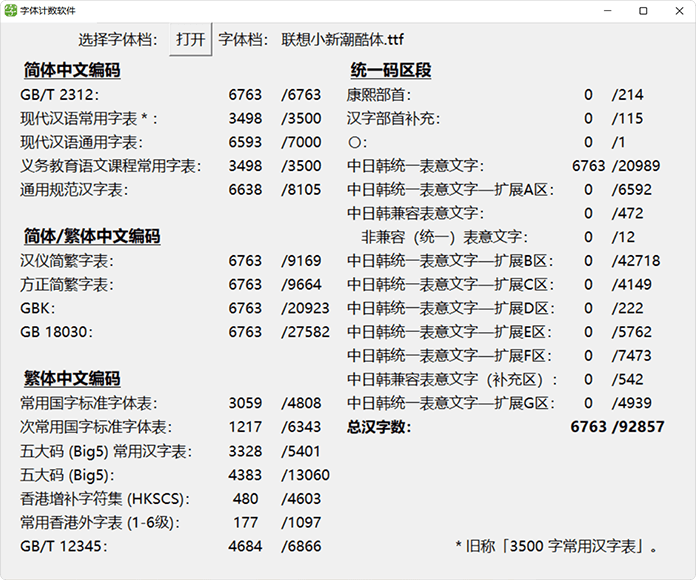
联想小新潮酷体:极智探索 字然进化 联想小新品牌定制字体上线
一款潮酷的黑体字,略窄的字面、纯直的结构、精简的笔画,使字体呈现年轻态和潮流感。
字面相对于常规字体缩窄,整体略瘦长,区别于传统黑体的方正感,更加年轻前卫、时尚新潮。
西文由直线与弧线构成,直线干净利落,曲线平滑流畅,风格沿袭汉字平切的收笔特征。
中西文混排,灰度均匀,具备流畅舒适的阅读体验。全套字体包括7766个字符,其中汉字6763个,西文符号等1003个,满足日常用字需求。